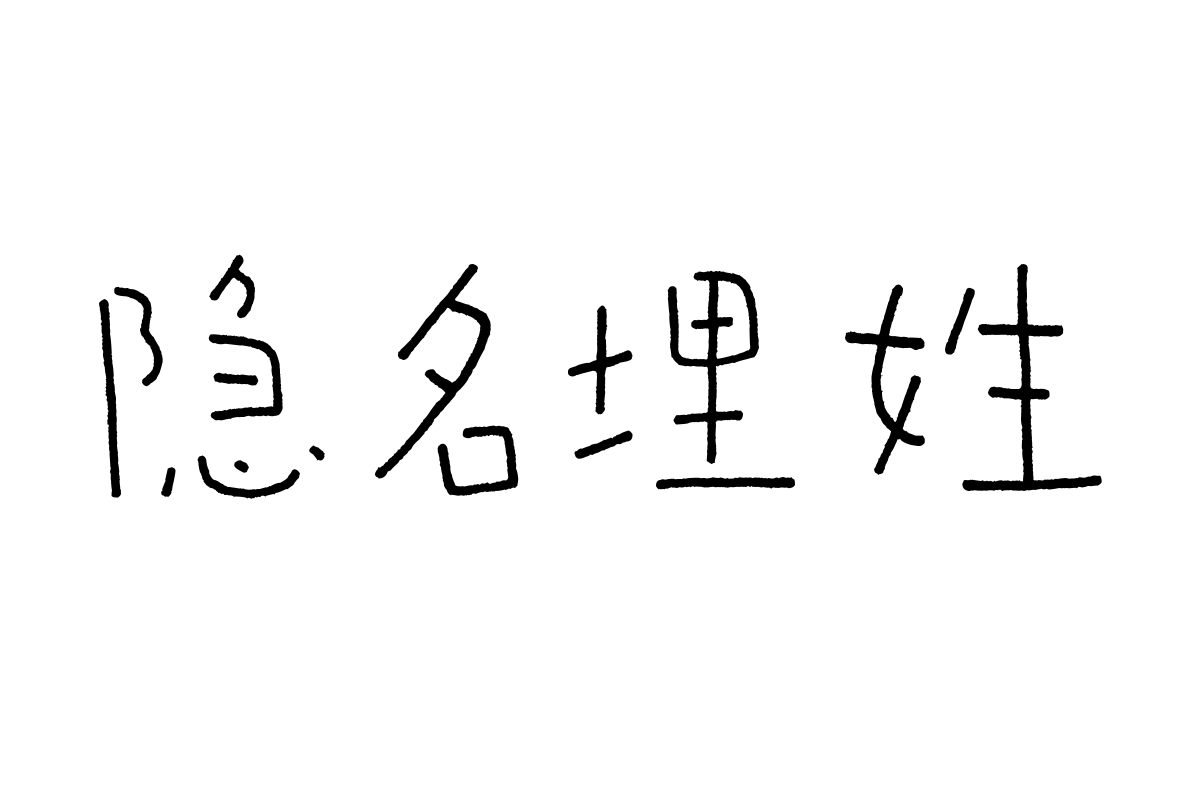
龚帆悦心体细是一套具有现代感的中文字体,由设计师龚帆创作。这套字体以其独特的设计和细腻的风格而闻名。它的特点是线条流畅、字形优美,给人一种优雅、精致的感觉。
龚帆悦心体细的笔画粗细适中,既有力度又有柔美,使得整个字体呈现出一种平衡感。它的字形结构紧凑,但不失空间感,使得整体看起来既紧凑又舒适。此外,龚帆悦心体细还注重细节的处理,如字距、行距等,使得整体布局更加协调。